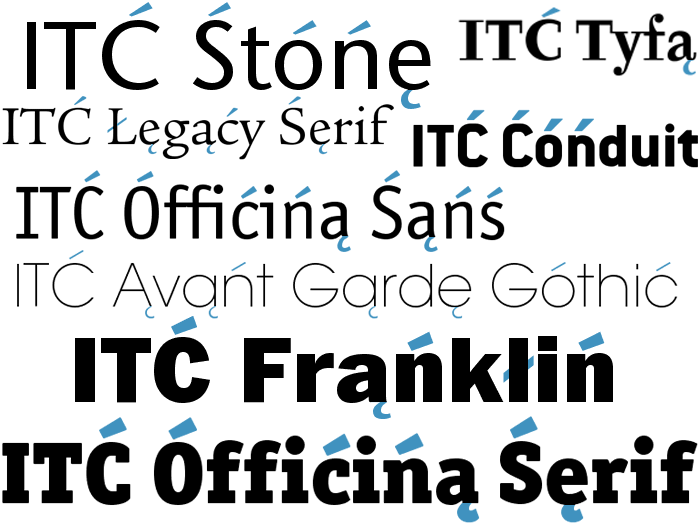
Firma International Typeface Corporation (obecne będąca częścią firmy Monotype) to od ponad 35 lat międzynarodowy lider w projektowaniu i sprzedaży krojów pism. ITC współpracuje ze światowej klasy projektantami dzięki czemu może zaoferować bibliotekę ponad 1650 krojów, zarówno klasycznych jak i modernistycznych. ITC licencjonuje swoją bibliotekę ponad stu trzydziestu firmom działającym w zakresach projektowania graficznego, technologii komputerowych i drukarskich.
ITC jako członek ATypI (Association Typographique Internationale) pomogła stworzyć standardy jakości projektowania, a także przyczyniła się do zwrócenia uwagi na etyczne aspekty związane z ochroną myśli twórczej i jej licencjonowania. ITC znana głównie z projektów klasycznych agresywnie rozszerzyła zakres swojej biblioteki krojów pism o projekty bardziej współczesne włącznie z wyróżniającymi się fontami tytułowymi i ilustracyjnymi. ITC poszerzając spektrum swojej kolekcji nabyła zestaw fontów tytułowych firmy Fontek, który był oryginalnie opracowany przez Letraset. Zestaw Fontek zawiera unikatowe kroje kilku wyśmienitych współczesnych projektantów. Połączenie zestawu Fontek i biblioteki ITC zaowocowało w postaci wyjątkowo wszechstronnej kolekcji ponad 1000 cyfrowych krojów pism.
Obecnie ITC opracowuje i wypuszcza na rynek około 100 fontów rocznie. Można obejrzeć wiele spośród tych nowych projektów w jej witrynie internetowej w dziale FontsNOW!; można nawet utworzyć próbkę z nowych krojów używając wirtualnej maszyny do pisania Euripides. Pracując nad rozwojem sztuki projektowania krojów pism w erze komputerów, ITC znacznie zrewidowała swój program odnośnie nowych edycji. Obecnie firma dokonuje systematycznego przeglądu przedłożonych projektów i zatrudnia renomowanego typografa - Colina Brignall'a w charakterze międzynarodowego „poszukiwacza”. ITC zoptymalizowała również swoje metody produkcji aby przyspieszyć publikację zaakceptowanych wzorów.
Wykraczając poza tradycyjny typ działalności ITC obecnie dystrybuuje również inne produkty cyfrowe włączając w to „Decorative Initials” i „Tone types” - pliki EPS, a także „ITC Design Elements” i „ITC Photo Web Tiles” na potrzeby stron internetowych. Witryna producenta może stanowić cenne źródło informacji typograficznych. ITC często aktualizuje tę witrynę o edycje nowych fontów, nowe artykuły i inne niespodzianki.